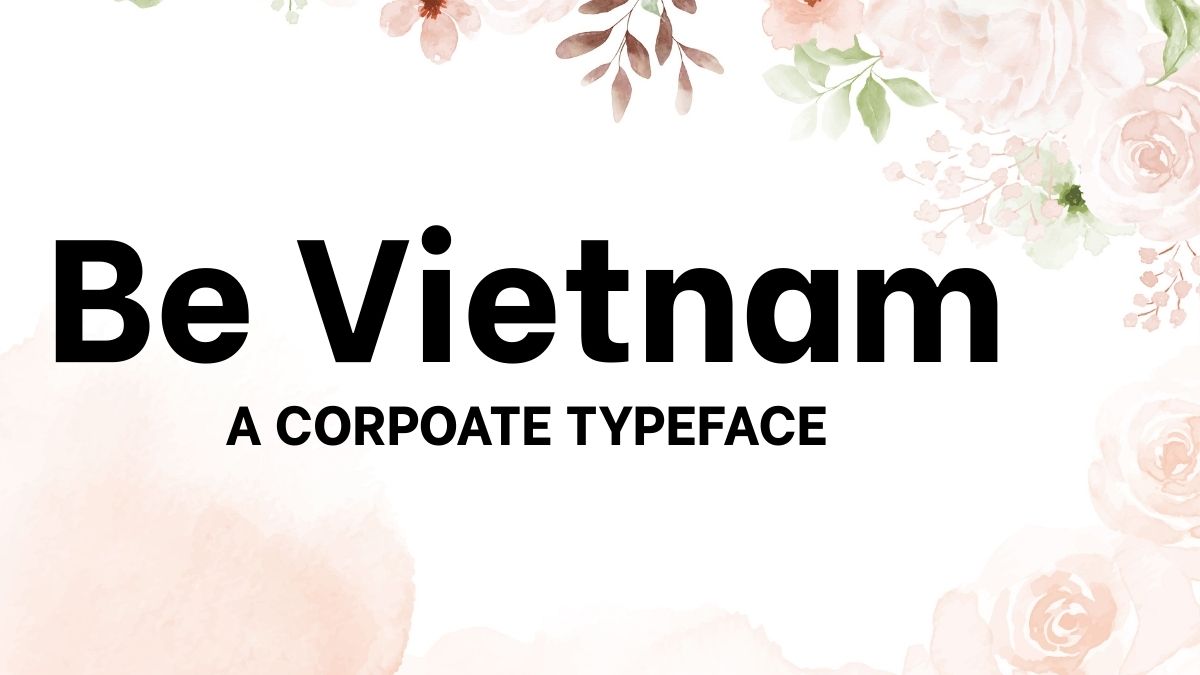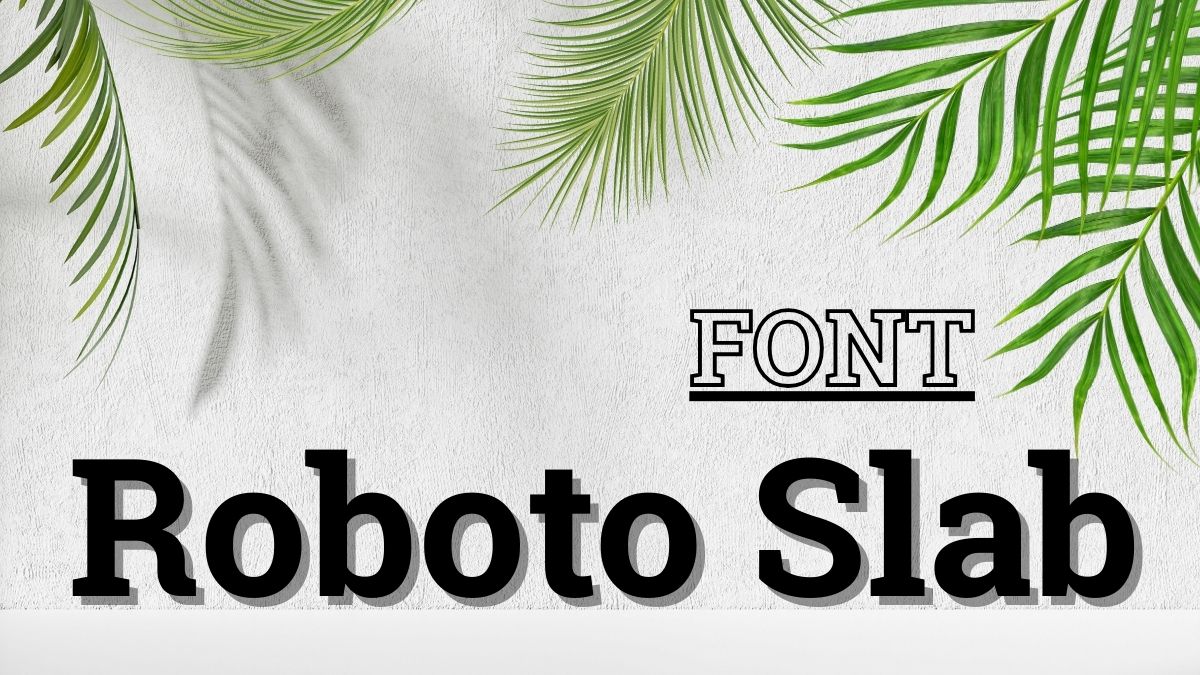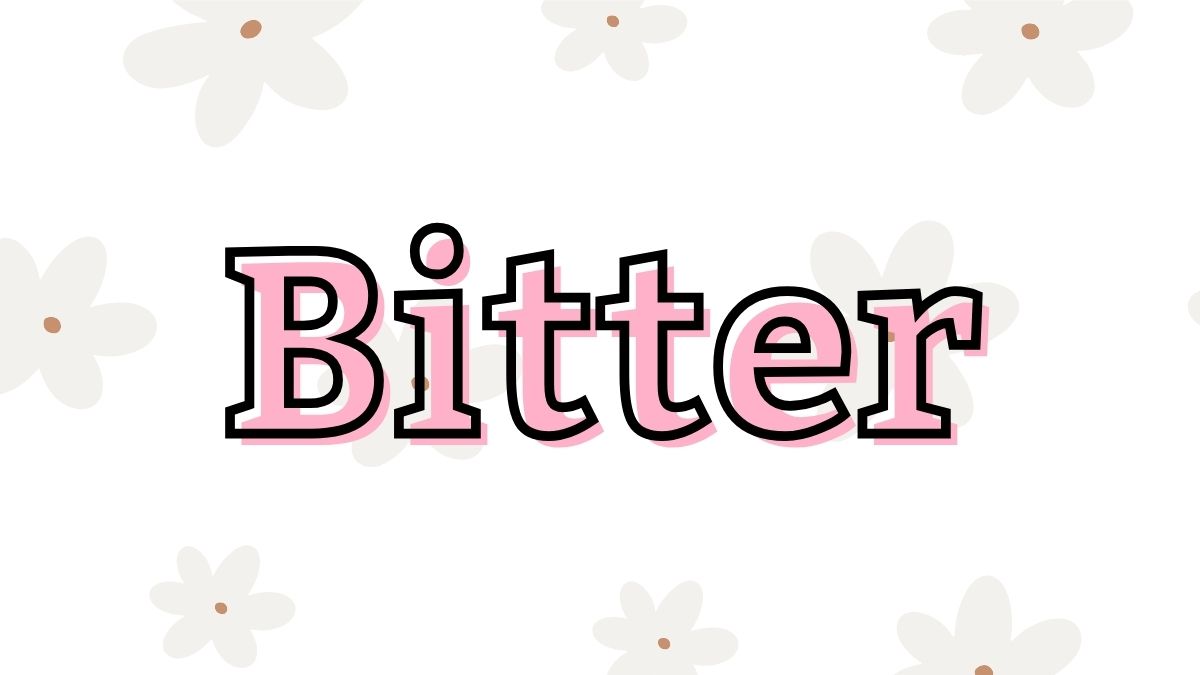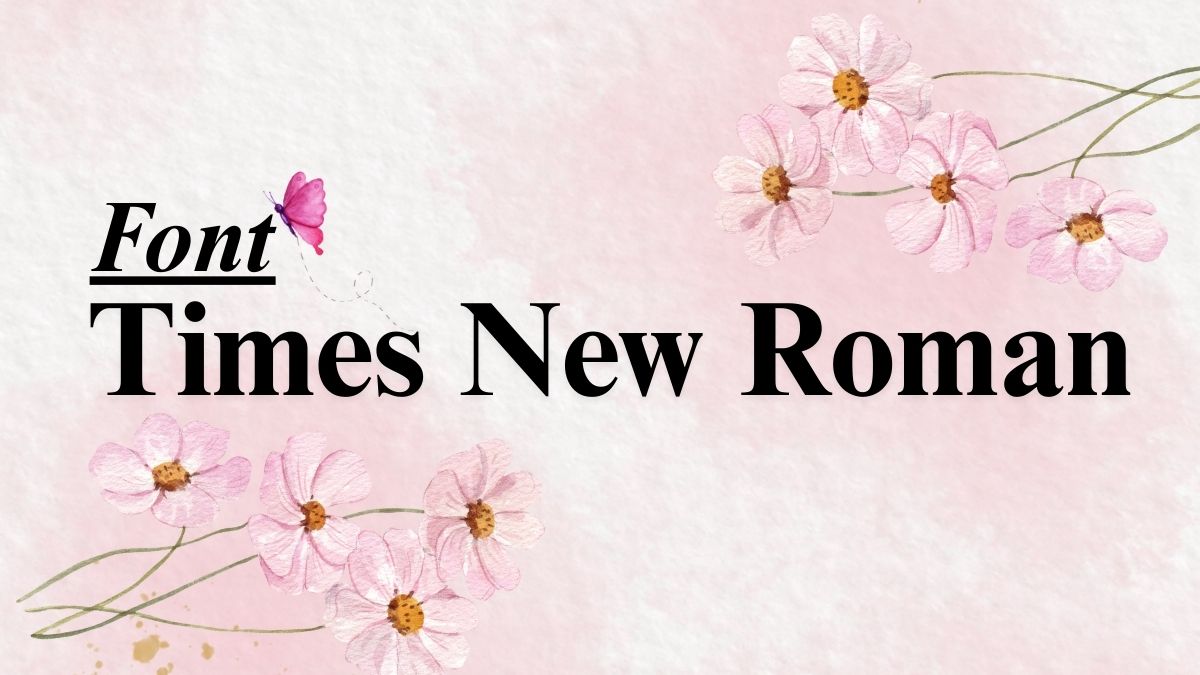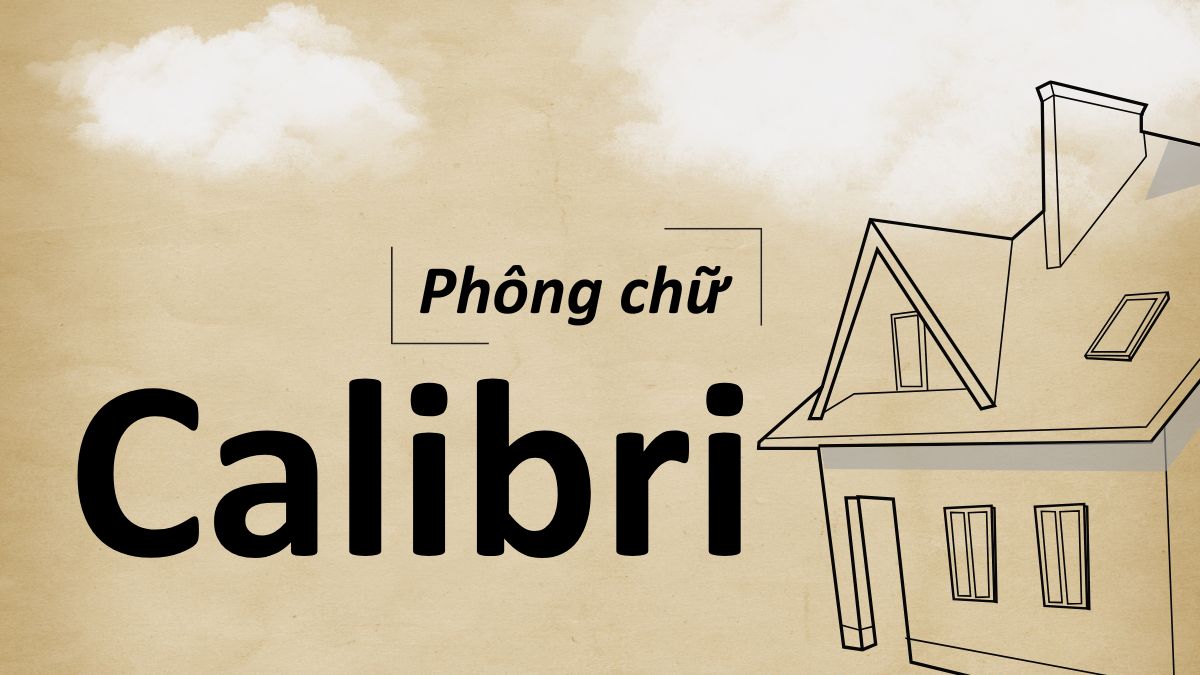
50+ Font chữ đẹp trong Word miễn phí và phổ biến 2026
Trong quá trình soạn thảo văn bản, việc chọn những font chữ đẹp trong Word không chỉ giúp nội dung dễ đọc hơn mà còn thể hiện sự chuyên nghiệp. Ngày nay, người dùng có thể lựa chọn đa dạng phông chữ, từ phong cách viết tay nghệ thuật, phông chữ hiện đại đến những font chữ văn phòng quen thuộc. Bài viết này sẽ giới thiệu chi tiết tất cả các font chữ trong Word để bạn dễ dàng tham khảo.
Tại sao nên chọn font chữ đẹp trong Word?
Một văn bản được trình bày với phông chữ đẹp trong Word sẽ gây thiện cảm ngay từ cái nhìn đầu tiên. Không chỉ tăng tính thẩm mỹ, lựa chọn đúng font chữ tiếng Việt đẹp trong Word còn giúp nội dung dễ hiểu và truyền tải thông điệp rõ ràng hơn.
Ví dụ, với các tài liệu học tập, nên chọn font chữ rõ ràng, dễ đọc, trong khi các mẫu sáng tạo lại phù hợp hơn với font chữ nghệ thuật. Việc thay đổi và kết hợp một số font chữ đẹp trong Word sẽ tạo sự đa dạng, giúp văn bản trở nên nổi bật và chuyên nghiệp.
Font chữ Việt hóa đẹp trong Word
Font chữ Việt hóa đẹp trong Word hỗ trợ đầy đủ dấu tiếng Việt, hiển thị rõ ràng và dễ đọc. Dưới đây là các font chữ đẹp trong Word được ưa chuộng cho cả văn phòng và thiết kế.
Be Vietnam
BBendigo mang phong cách độc đáo và táo bạo, rất phù hợp cho những thiết kế cần sự nổi bật như poster, logo, banner hoặc thiệp mời. Với Be Vietnam, văn bản trở nên rõ ràng, dễ đọc, đồng thời vẫn giữ được nét trẻ trung, hiện đại, mang lại cảm giác thân thiện và dễ tiếp cận cho người xem.
Roboto
Roboto nổi bật nhờ sự cân đối và khả năng hiển thị tốt trên mọi màn hình. Đây là phông chữ trong Word thường được chọn cho tài liệu dài bởi dễ nhìn, không gây mỏi mắt. Với nhiều kiểu chữ như Roboto Regular, Bold hay Italic, người dùng dễ dàng kết hợp để tăng tính thẩm mỹ.
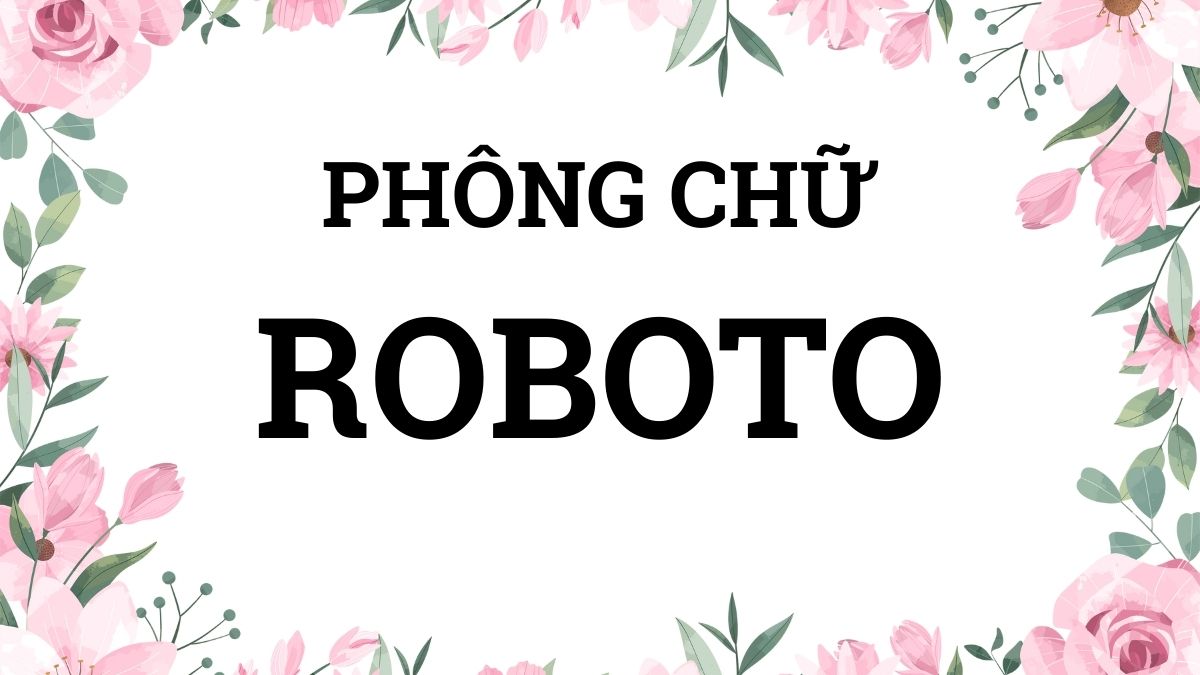
Source Sans Pro
Phông chữ Source Sans Pro là font chữ đầu tiên của Adobe dành cho giao diện, thường được dùng trong Word cho báo cáo, tài liệu học thuật và văn bản chuyên nghiệp. Với sự hài hòa trong từng đường nét mềm mại và cân đối, phông chữ này đem đến trải nghiệm đọc tự nhiên và thoải mái.
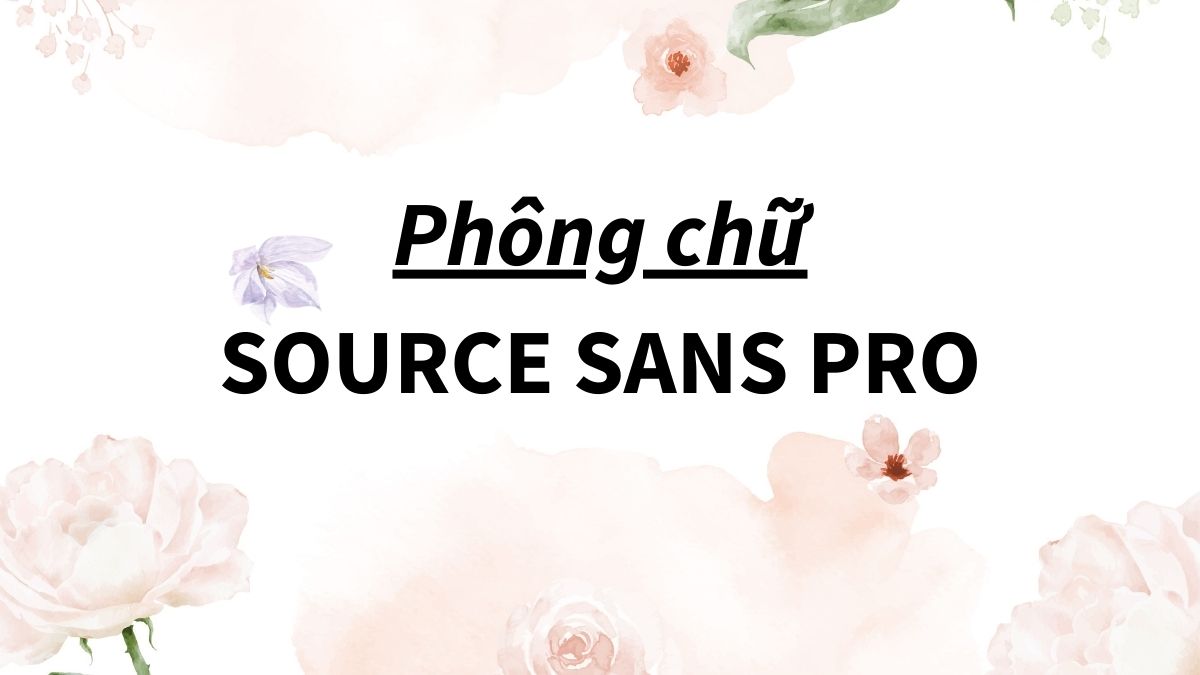
Open Sans
Open Sans mang đến sự cân bằng giữa hiện đại và tính ứng dụng cao. Đây là phông chữ đẹp trong Word được nhiều doanh nghiệp chọn để trình bày báo cáo hoặc sáng tạo profile. Nhờ khả năng hiển thị tốt, Open Sans luôn nằm trong top font chữ đẹp nên dùng.
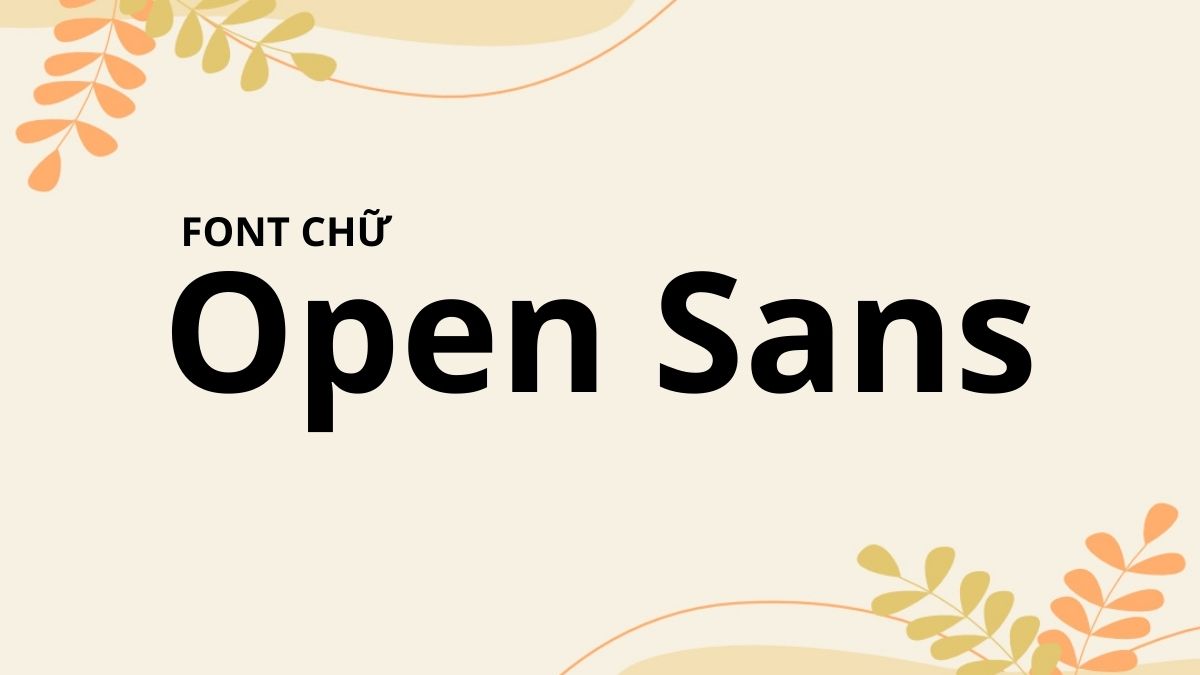
Playfair Display
Khác với những font hiện đại, Playfair Display mang nét cổ điển và sang trọng, thường dùng cho tiêu đề hoặc nội dung quan trọng. Với đường nét thanh mảnh nhưng dứt khoát, font này tạo cảm giác tinh tế, phù hợp cho tài liệu học thuật, báo chí hay ấn phẩm cần sự trang nhã.
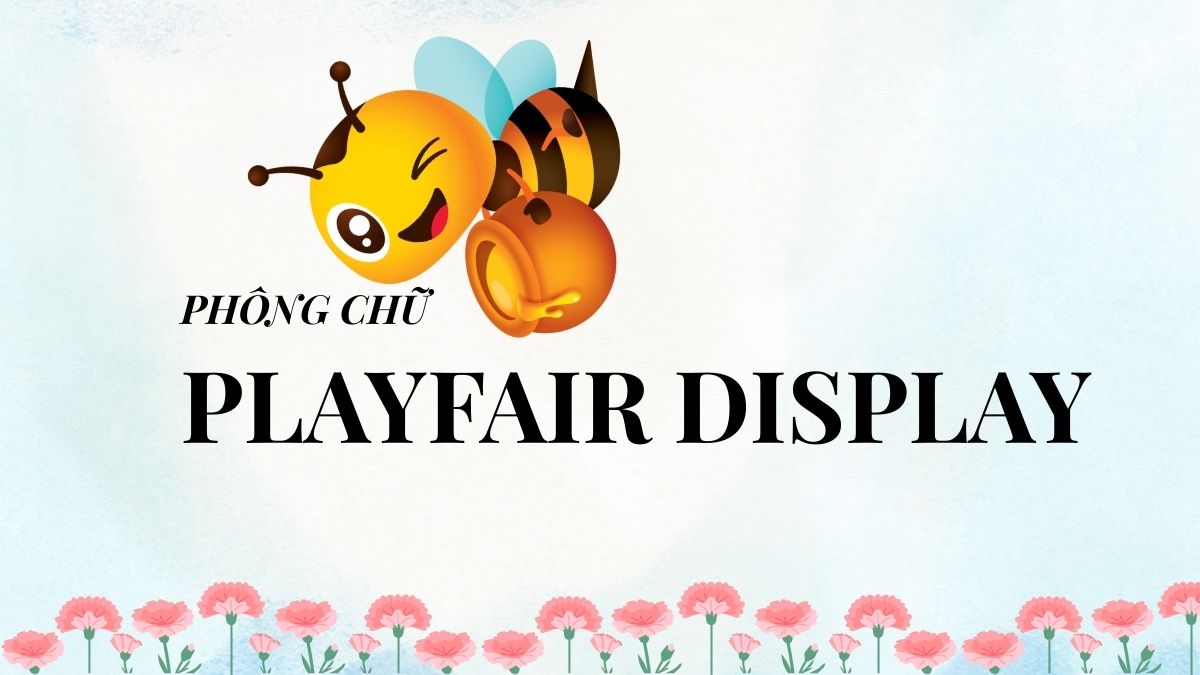
Font chữ viết tay trong Word
Nhóm font chữ viết tay trong Word được yêu thích bởi sự mềm mại, gần gũi và giàu tính thẩm mỹ. Dưới đây là một số font chữ đẹp trong Word rất phù hợp khi thiết kế thiệp, poster hoặc các tài liệu sáng tạo.
Pacifico
Pacifico mang phong cách tự do, phóng khoáng, tạo cảm giác tươi mới và đầy cá tính cho văn bản. Đây là một trong những phông chữ đẹp trong Word được nhiều người yêu thích khi muốn làm nổi bật sự trẻ trung, năng động trong thiết kế nội dung.
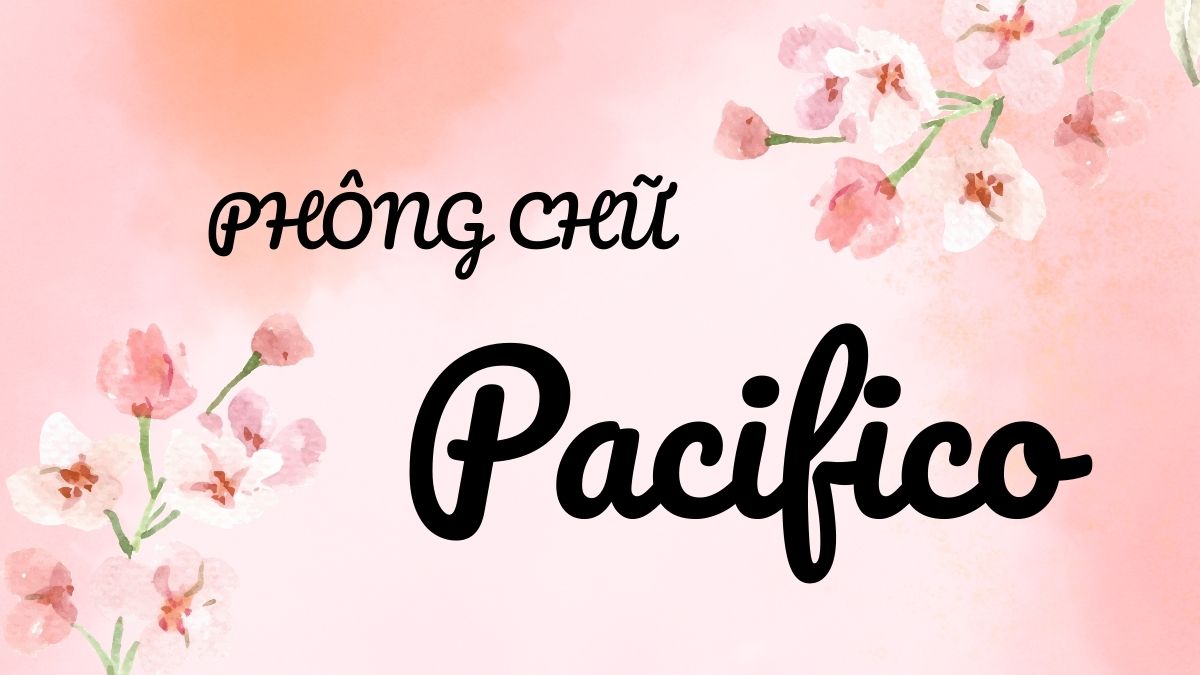
Dancing Script
Với đường nét uyển chuyển như chữ viết tay mềm mại, Dancing Script mang lại cảm giác gần gũi, nhẹ nhàng nhưng vẫn tinh tế. Đây là một font chữ đẹp trong Word phù hợp cho tiêu đề, lời chúc hoặc các dự án cần sự mềm mại và nghệ thuật.
Charmonman
Charmonman là font chữ Việt hóa độc đáo, được thiết kế riêng để hỗ trợ tối ưu cho tiếng Việt với các dấu và ký tự hiển thị mượt mà. Font này mang lại sự sáng tạo cùng cá tính rõ rệt, rất phù hợp khi bạn muốn tạo ấn tượng trong các thiết kế hoặc bài viết.
Srisakdi
Srisakdi gây ấn tượng bởi nét chữ mềm mại, duyên dáng và đầy tính nghệ thuật, mang đến cảm giác sang trọng cho văn bản. Đây là một font chữ đẹp trong Word rất phù hợp khi thiết kế thiệp, lời mời hoặc các tài liệu cần sự khác biệt.
Dưới đây là tất cả các font chữ trong Word phổ biến, thường xuyên xuất hiện trong công việc, báo cáo và học tập. Sự đơn giản, dễ đọc của phông chữ là ưu điểm lớn nhất.
Nên dùng font Serif hay Sans Serif?
Nên dùng Font Serif nếu muốn tạo cảm giác trang trọng và phù hợp cho tài liệu nhiều chữ hoặc văn bản học thuật. Ngược lại, Sans Serif mang phong cách hiện đại, dễ nhìn trên màn hình và được nhiều người chọn trong các font chữ đẹp trong Word.
Font nào phù hợp làm báo cáo?